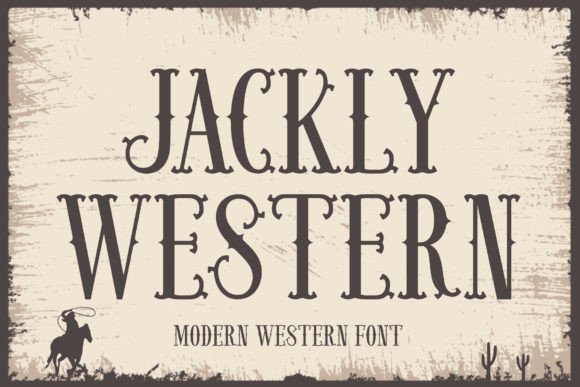
Jackly Western
Trouver les bons éléments de conception peut être un défi, mais Jackly Western propose une collection exceptionnelle qui rehausse instantanément votre travail.
Que vous créiez des produits POD (impression à la demande), des invitations de mariage ou des visuels pour les réseaux sociaux, Jackly Western est un choix idéal.